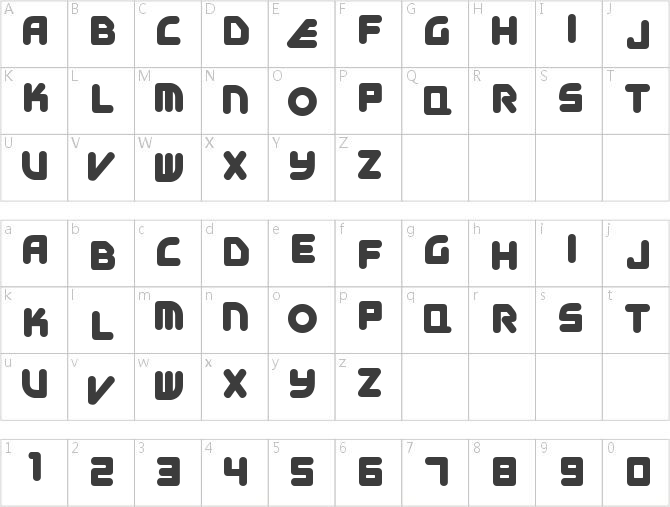
EFour Digital Font 詳情頁
字體名稱: EFour D
EFour Digital Font
EFour Digital Font字體字庫是一款讓人賞心悅目、百看不厭的英文字體,適合各類廣告和產品包裝設計應用,字體大小0.03MB,格式為ttf字體,上傳用戶是23KUN,作者/版權方為未知